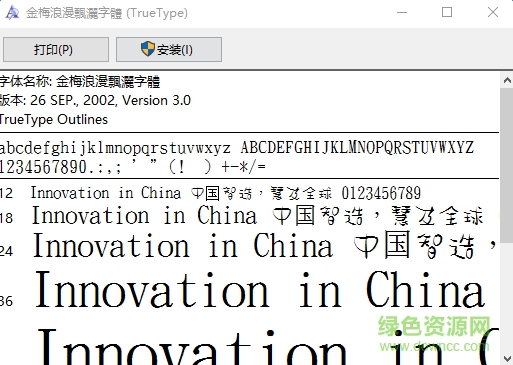
金梅浪漫飄灑字體是金梅字庫中很有特色的一款字體,這款字體寫出來的字是很好看的,瀟灑飄逸,不拘一格的風(fēng)格,可以用在很多方面,喜歡這款字體的朋友可以來綠色資源網(wǎng)下載。
這款字體是真的很好看,有著自己獨(dú)特的風(fēng)格,用來寫字是很不錯(cuò)的,大家可以去試試看哦。